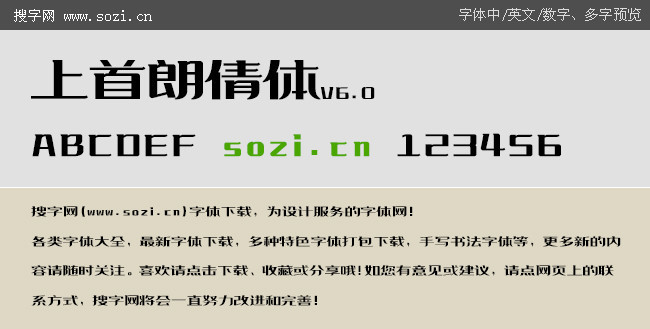
上首朗倩體V6.0
搜字網(wǎng)給大家提供一款上首朗倩體V6.0中文字體下載,上首朗倩體字體筆畫柔潤,加注了一些帶有活潑色彩的圓潤小勾角,整體體型扁平,橫筆豎筆粗細(xì)明顯,橫細(xì)豎粗,部分結(jié)構(gòu)進(jìn)行了導(dǎo)圓處理,這款為升級(jí)版本。適用于搭配標(biāo)志、廣告標(biāo)語、商業(yè)廣告等廣告設(shè)計(jì)。